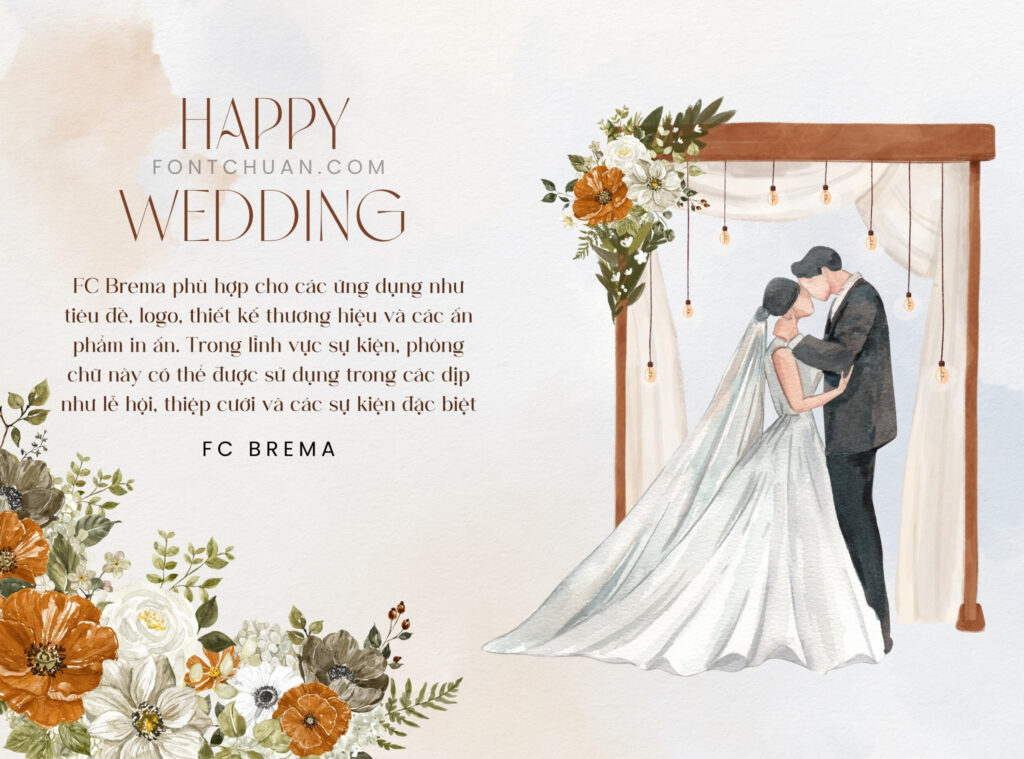
Font Brema là một phông chữ sans-serif hiện đại với thiết kế hình học độc đáo. Được tạo ra bởi Andrey Sharonov, phông chữ này mang lại cảm giác tươi mới và sáng tạo, phù hợp cho nhiều dự án thiết kế khác nhau.
Font Việt hóa Brema trên thị trường rất khó để tải được vì vậy Nhóm Font Chuẩn đã tiến hành Việt hóa miễn phí 100% hỗ trợ đầy đủ các ký tự tiếng Việt, giúp người dùng dễ dàng áp dụng trong các dự án sáng tạo.
Với thiết kế hình học và hiện đại, FC Brema VIP phù hợp cho các ứng dụng như tiêu đề, logo, thiết kế thương hiệu và các ấn phẩm in ấn. Trong lĩnh vực sự kiện, phông chữ này có thể được sử dụng trong các dịp như lễ hội, thiệp cưới và các sự kiện đặc biệt. Đặc biệt, khi sử dụng làm font chữ Tết, Brema có thể mang lại sự hài hòa giữa hiện đại và không khí truyền thống, rất thích hợp cho các ấn phẩm mùa xuân như bao lì xì, poster hay banner Tết.
Ngoài ra, nhờ thiết kế hình học hiện đại và thanh thoát, FC Brema VIP không chỉ lý tưởng cho các ấn phẩm thương hiệu, poster, tiêu đề, mà còn có thể sử dụng như một Font chữ Giáng Sinh để trang trí thiệp, banner hay poster Giáng Sinh.